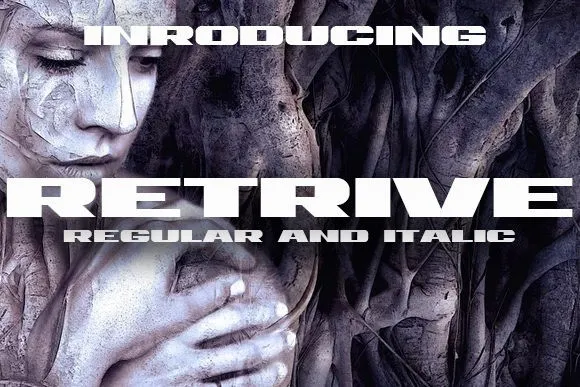
Aqui está uma descrição em português para a página de download da font ‘Retrive Font’, categorizada como sans serif: Através do site 99designs, esta é uma fonte sans-serif que captura um look moderno e criativo sem perder elegância. Fabricada por Vladimir Nikolic, Retrive apresenta linhas diferentes e pontos de junção distintos, dando ao texto um visual moderno e vibrante. Ideal para headlines, posters ou sinalizações, Retrive é perfeita para qualquer projeto gráfico que deseja destacar-se com uma impressão duradoura. Com seu design minimalista mas não menos atraente, Retrive está à altura de criar uma experiência visual diferenciada e inovadora em seus projetos. Seja você um designer gráfico ou um artista digital, retorne sempre ao Retrive para encontrar aquela fonte que completa sua arte criativa.